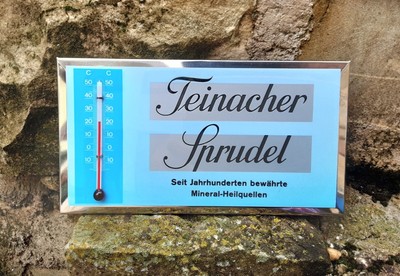
50er-Jahre-Schrift?
kann mir jemand ein oder zwei typische Fonts, die in den 50er Jahren in der Werbung benutzt wurden, nennen. Es soll ein Etikett für Mineralwasser gestaltet werden, das aber auf Anhieb in den 50ern verortet werden soll.
Mit der Abbildung grenzdebil grinsender junger Damen machste nix verkehrt, schön anti-feministisch und frauenverachtend. Dann kennt man die 50er-Jahre gleich wieder.
Typische Fonts der 50er in der Werbung gibt es nicht, es war alles dabei.
Die von mir verlinkte Liste "1950er-Jahre-Schriften" ist auch wenig aussagekräftig, da sie in den 50ern erschienene Schriften beinhaltet. Die wurden nicht zwangsläufig auch vermehrt angewendet.